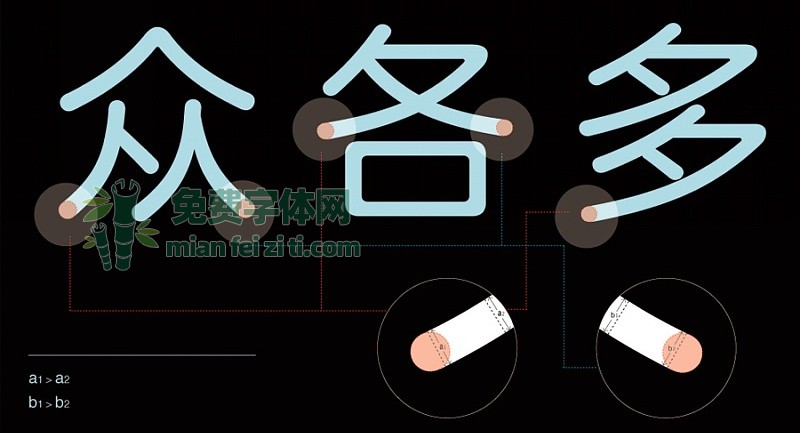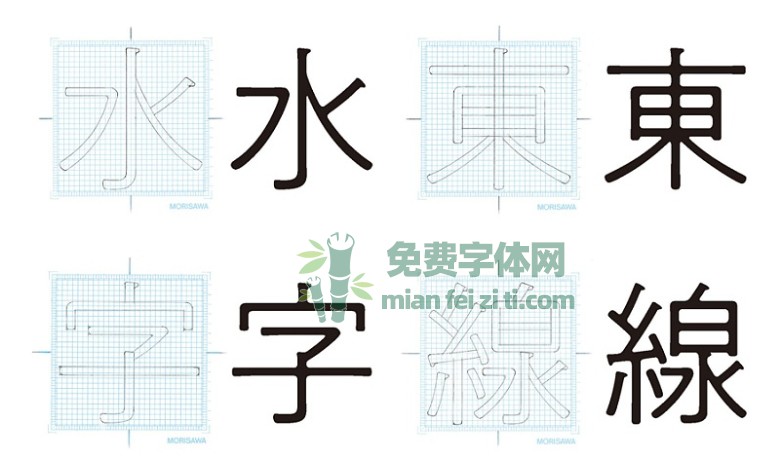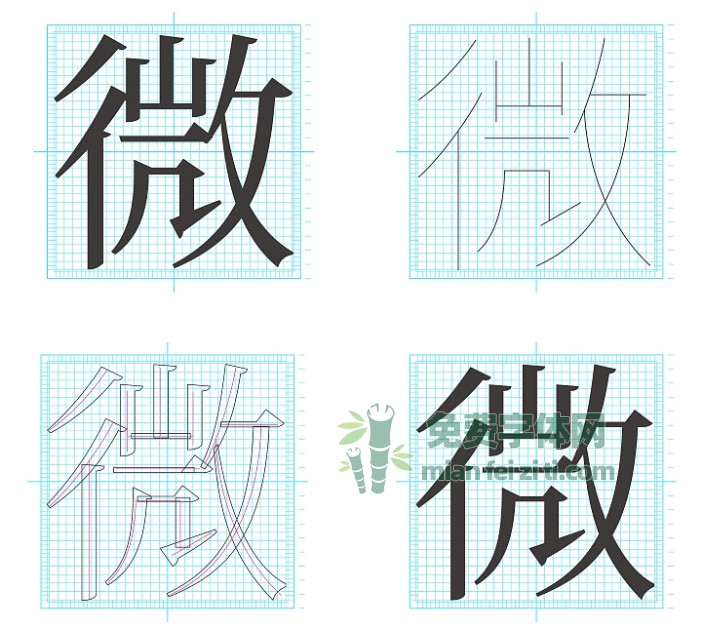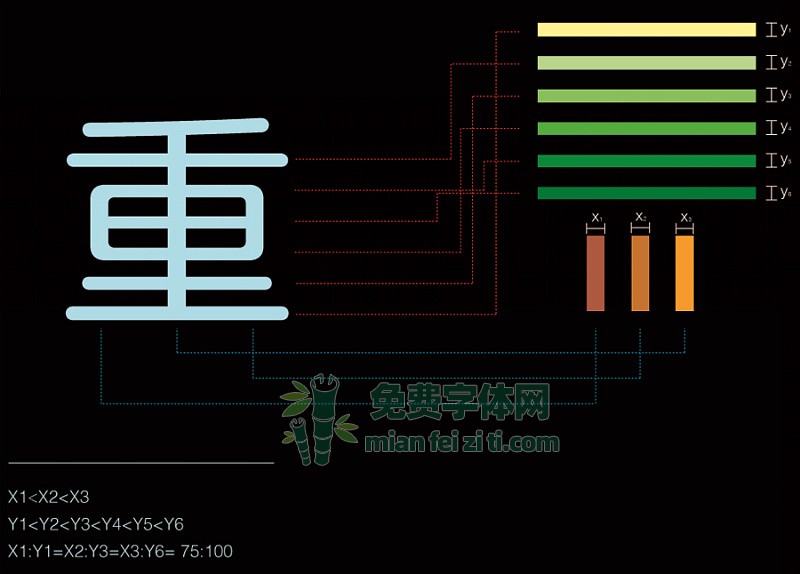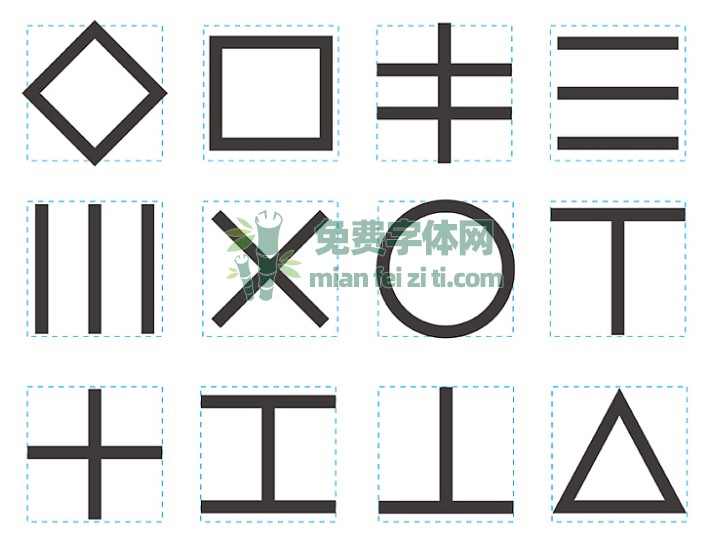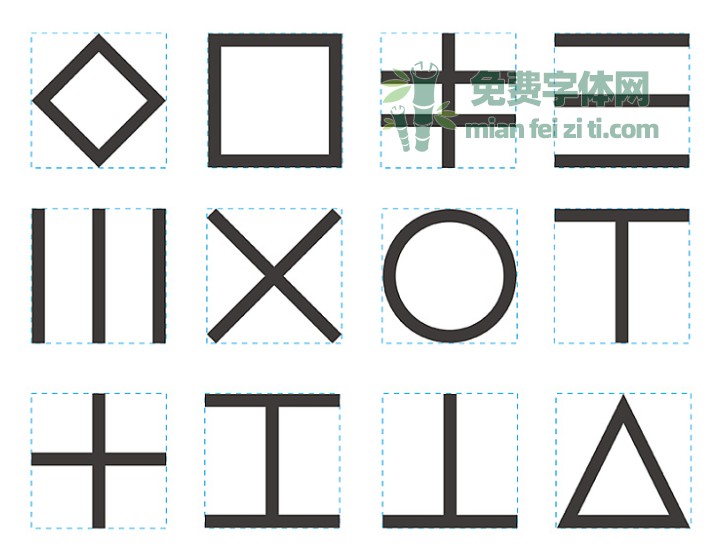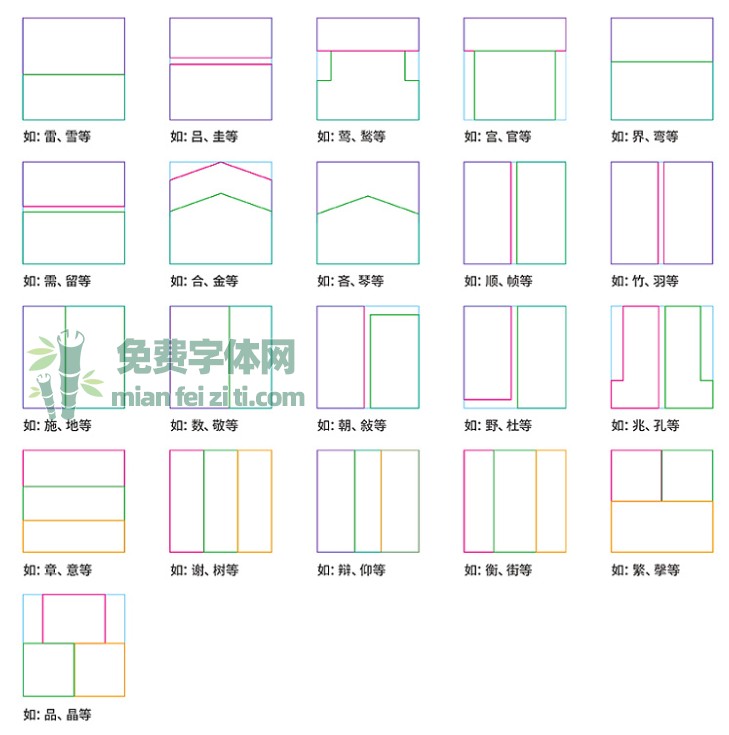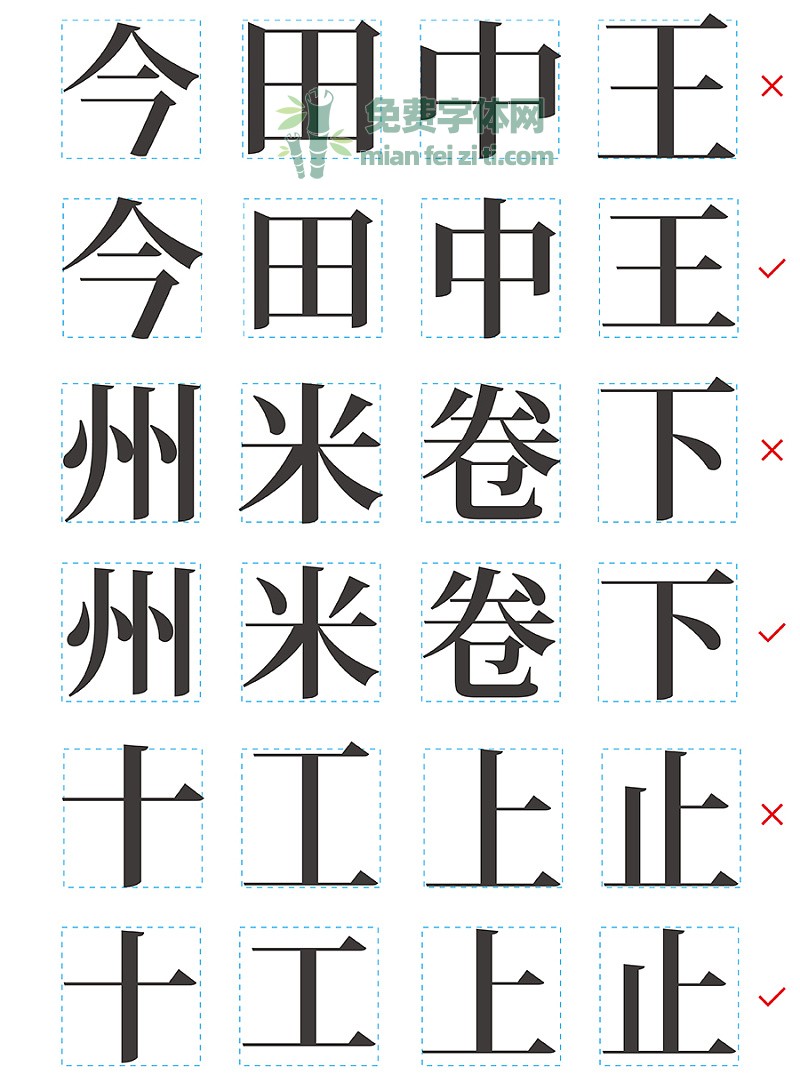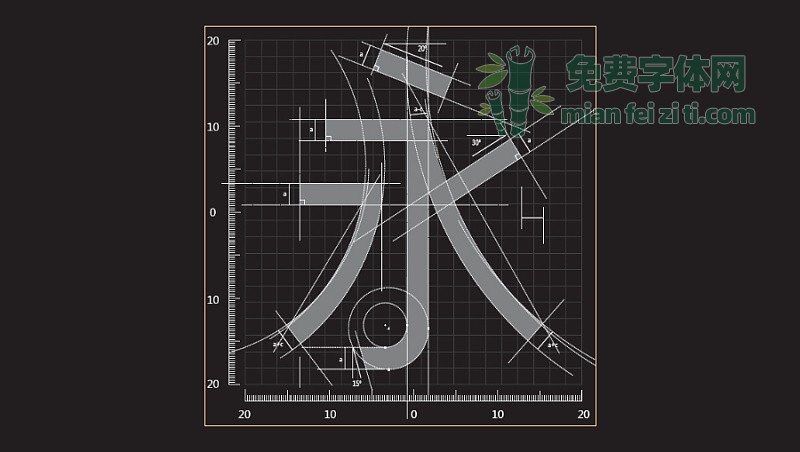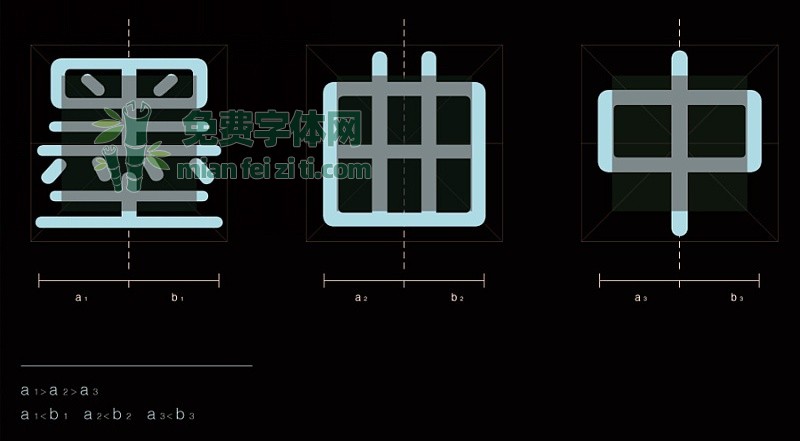
近些年,字体设计越来越火热,很多小伙伴急于求成跳过了汉字基础知识的学习,直接上手做起了字体设计,很多基础性的错误越来越常见。这也是我写这篇文章的初衷,希望对初学者有所帮助。
1. 汉字的发展简史
2. 字体基本笔划
3. 字体基本常识
4. 永字八法
5. 字体间架结构
6. 字形的错视
7. 字形的大小调整
8. 笔划粗细的调整
9. 重心的调整
10. 第二中心线
11. 通用字形
12. 从临摹到创造
13. 通用字形学习方法
14. 宋体字与黑体字学习方法
15. 字库字体细节赏析
汉字的发展简史
通过图文的形式直观的了解下汉字的发展史。
字体基本笔划
宋体字作为示范例子:
字体基本常识
以「井」字为例,如下图:
永字八法
所谓「永字八法」,传说是僧智永将王羲之兰亭序里的第一个字「永」的情态分为侧、啄、磔(zhé)、努、勒、策、掠、趯(yuè)最基本的笔划动作,作为学习书法的实例。因此永字八法可以作为初学书法结构的标准,尤其在汉字的字体设计中,可用来研究各种文字的构成,从而制作出美好的字态。
字体间架结构
汉字的种类众多,笔划有多也有少,空间的排布就尤为重要。
字体的间架结构可分为两类:
1. 独体字
2. 合体字
字形的错视
视觉心理是很奇妙的,因而为我们所运用,然而,文字中笔划的粗细、长短、方向、位置等会产生不和谐不平衡的现象,因此要做一些细微的调整。
1. 线粗细的错视
左侧为横竖两个笔划,他们是等宽的两笔,仔细观察可以发现在视觉上横画要比竖画宽一些。所以,为了达到视觉上的等宽,工字的竖画要加宽一些。
2. 正方形的错视
通常做一个正方形的字,会将字面框定位正方形,但是做出来的字在视觉上却是长方形的。所以,想要做成正方形的字,字面框要将正方形压扁一点。
3. 垂直分割线的错视
两条粗细、长短相同的线段,垂直平分为T字形,其中被分割的线段,在视觉上要显得短一些。所以,要将竖线缩短一些。(例如:上、下字形)
4. 水平线被二等分的错视
一条线段被二等分后,在视觉上左侧要比右侧长一些。所以,为了达到视觉上的等分,分割点要左移一些。(例如:十、大字形)垂直线的二等分也是同样的道理。
5. 横竖线的错视
下列两组线条,一横一竖,所形成的正方形是一样大小的,但是,在视觉上横线一组显得瘦高,竖线一组则显得扁矮。这也是为什么「王」「川」会这样调整的原因。
字形的大小调整
汉字的字形众多,但有些字形在视觉上会产生大小的变化,因此,要对症下药。
下图为未作调整的字形简图:
调整后的字形简图:
实例如下:
笔划粗细的调整
我们设计字体时都要在相同的字格中进行,无论笔划的多少都要写在格中,为了达到黑白空间的平衡。那么,就有了笔划粗细问题和布白的问题。字形粗细处理原则:
1. 横细竖粗
上文视错中详细介绍了原因,在视觉习惯上要求横细竖粗。
2. 主粗副细
多笔划的字切记平均等粗,应主次分明,主笔粗,副笔细。
3. 外粗内细
内包的字一般都是以外粗内细的方法来处理,围笔划的粗细,要保持在基础笔划的黑度。与三结合多笔划的字中间要减细。
4. 疏粗密细
对疏密不均匀的组合结构字,需疏粗密细的做加减法,要密不拥挤,疏不薄感。
5. 交叉减细
凡横竖撇捺交叉的字,交叉点会显得特别黑,需做减细的处理。
重心的调整
提到重心就要引出与其相对应的名词,叫做中心。中心指的是字幅框几何中心的交点,它是实际存在的点,我们在设计字的时候通常以中心来调整字重心的位置,而不是将二者混为一谈。(如下图)
通常重心要比中心略高些,在设计字体时,不同的重心又会赋予字形不同的性格。重心高的字有轻、瘦、雅的感觉,重心低的字有稳、厚、拙的印象。
下图实例,提醒大家设计字体时重心要保持平稳,不要忽高忽低。
第二中心线
谢培元在1962年从实际工作当中归纳总结的。任何形声组合字或复合结构的字都是可以找到两条中心线的,这两条中心线可以帮助我们在设计时快速的确定部件的位置。形旁和声旁这两个部件的中心距离越大,字面就越大,反之,字面就越小。这是掌控形声组合字或复合结构字大小的一个有效工具。
通用字形
「通用字形」这个概念是在迟同斌(开心老头)老师的书中提及的,它的特点如下图所示:
其实原理就是将笔划外空间缩小从而放大中宫,那么中宫指的是汉字笔划围成的空间,下图以九宫格的形式展示出中宫大的好处,A要比B舒展些,B显得紧凑些,随着从大到小的变化,舒展和紧凑的感觉会增加。
近些年这种字形越来越常见,设计师也频繁使用这种字形,字体公司也不断推出这种结构的字体,虽然他们在体饰上各不相同,但结构原理都是相同的。
从临摹到创造
大家都知道人类是世界上最善于模仿的动物,人类的最初知识,也是从模仿中得来的,我们可以说模拟是求知,因此,学习字体设计也唯有从临摹入手了。例如日本这个国家,就是一个非常善于学习、临摹的国家,他们的文字、茶艺都是学习我们国家的,尤其是字体设计中的宋体类(日本称之为明朝体),可以说起源于中国兴盛于日本,可见学习、临摹的重要性。
通用字形学习方法
通用字形只需要掌握结构骨架就可以,体饰可以加入自己的想法。
宋体字与黑体字学习方法
使用日本森泽字体公司原稿网格从画骨架、勾轮廓、填黑的方式临摹宋体字,这种网格的优势在于很好的定位笔划的位置,而且临摹宋体字既能对宋体字的结构与笔划特征深入理解,又能对曲线的弹性与调整方法有所理解。(下图宋体字为小塚宋体等宽)
根据笔划结构整理出下面的临摹字样,供大家临摹使用。
下图为森泽字体公司的黑体草稿:
字库字体细节赏析
细节决定了字体的优美与否(下图为方正兰亭圆体)。
啰嗦了这么多,大伙应该对字体有了重新的认识。基础性的问题再出现,应该不难发现了吧?下图的几组字体的问题,你看出来了吗?下图案例来源于网络。